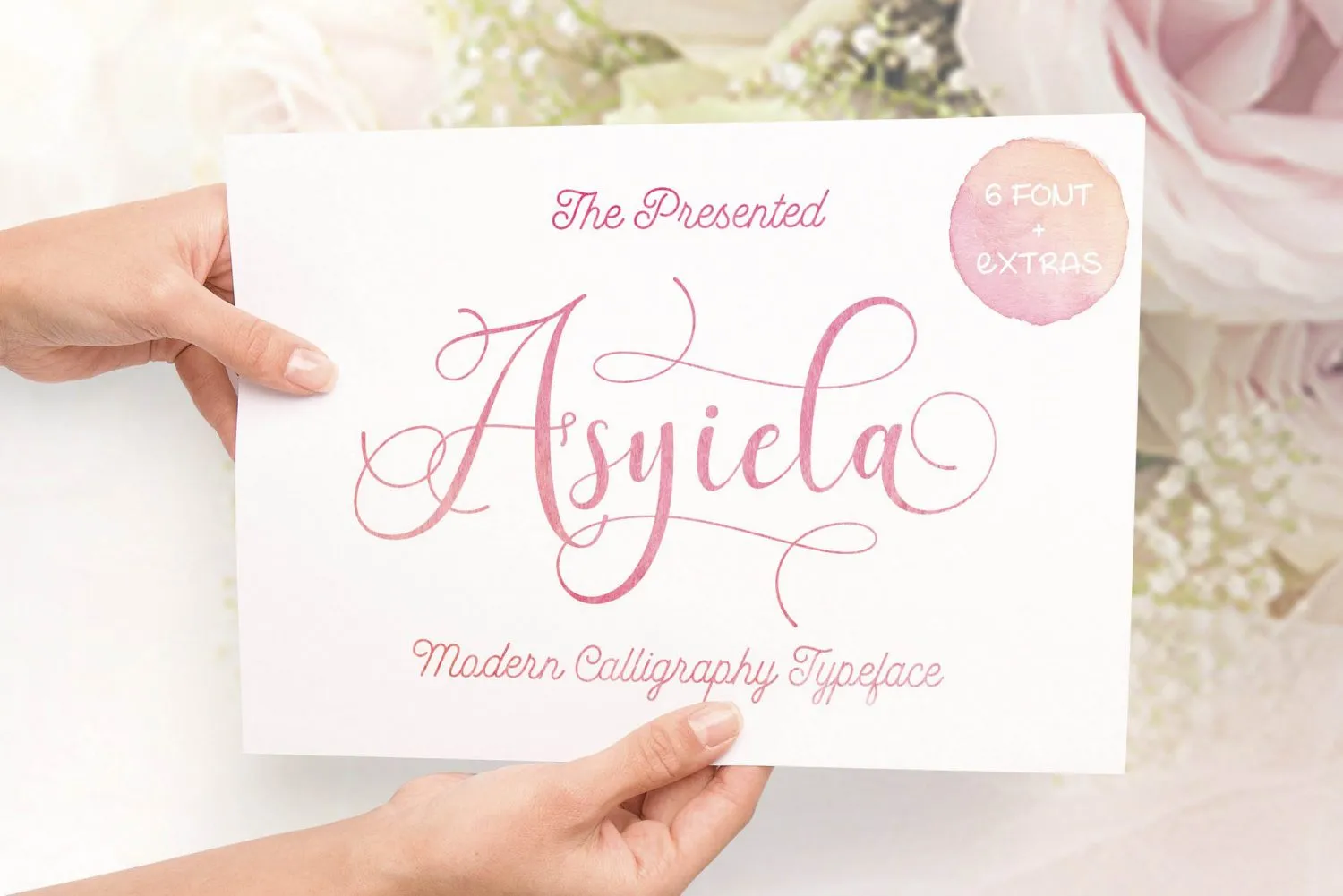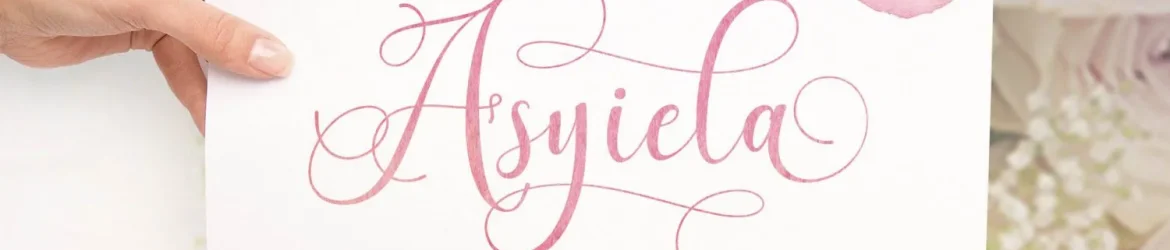
Descubra AsyielaScript Font aqui! Especificamente projetada para designers, este script premium foi criado por Letterme Co e está disponível gratuitamente no creativemarket. AsyielaScript é uma fonte Script que traz consigo um toque de amor e beleza artística, perfeita para qualquer projeto que exija um ar sofisticado e único. Ideal para festas como casamentos e aniversários, produtos cosméticos, moda ou designs onde se deseje criar um visual elegante e diferenciado. AsyielaScript está disponível em versões tradicionais e inclui uma variante desfocada, além de adoráveis flores e ornamentos. Torne seus projetos ainda mais especiais com AsyielaScript Font, sua fonte Script ideal para todas as ocasiões especiais ou qualquer projeto que você esteja criando.